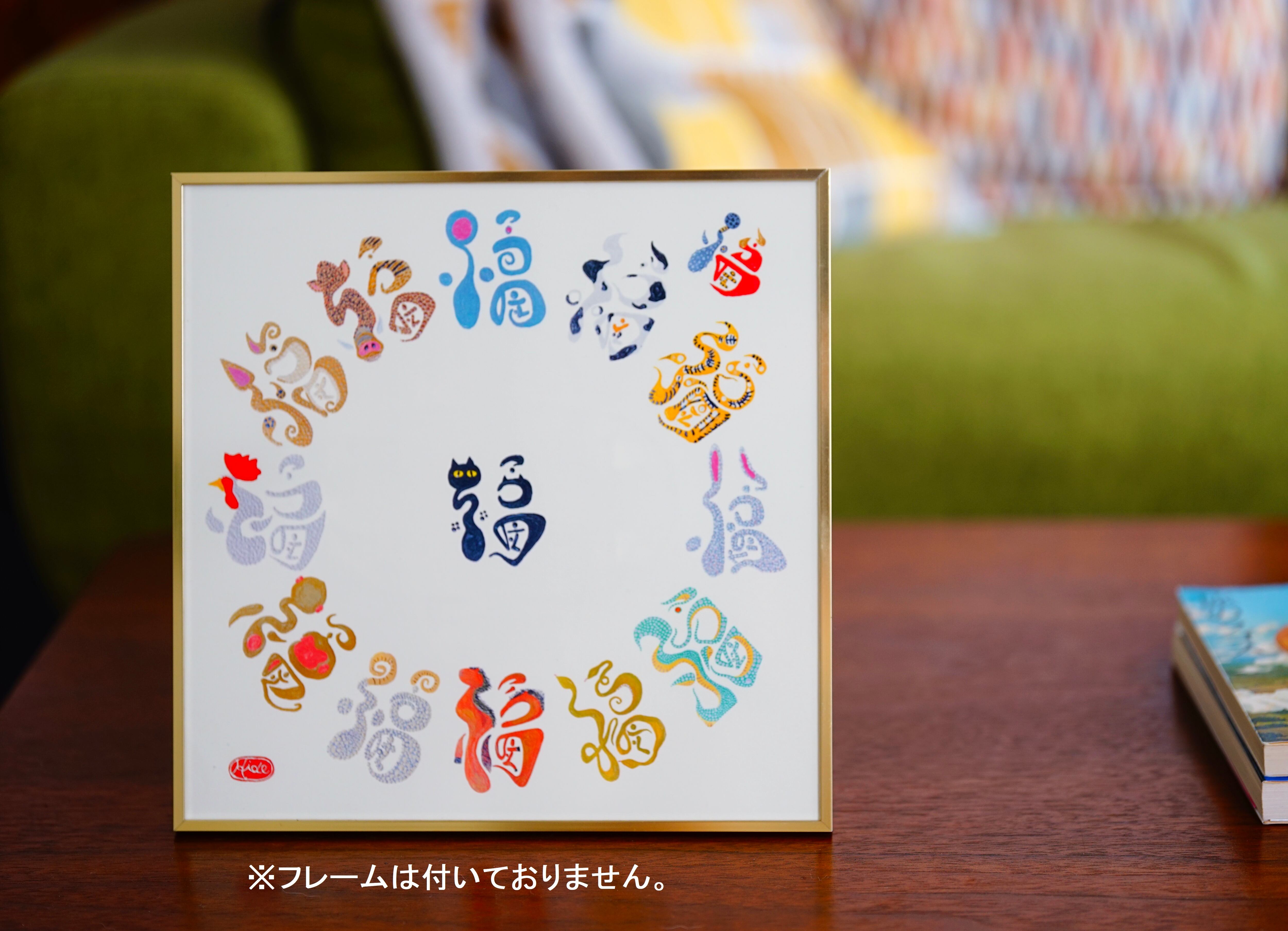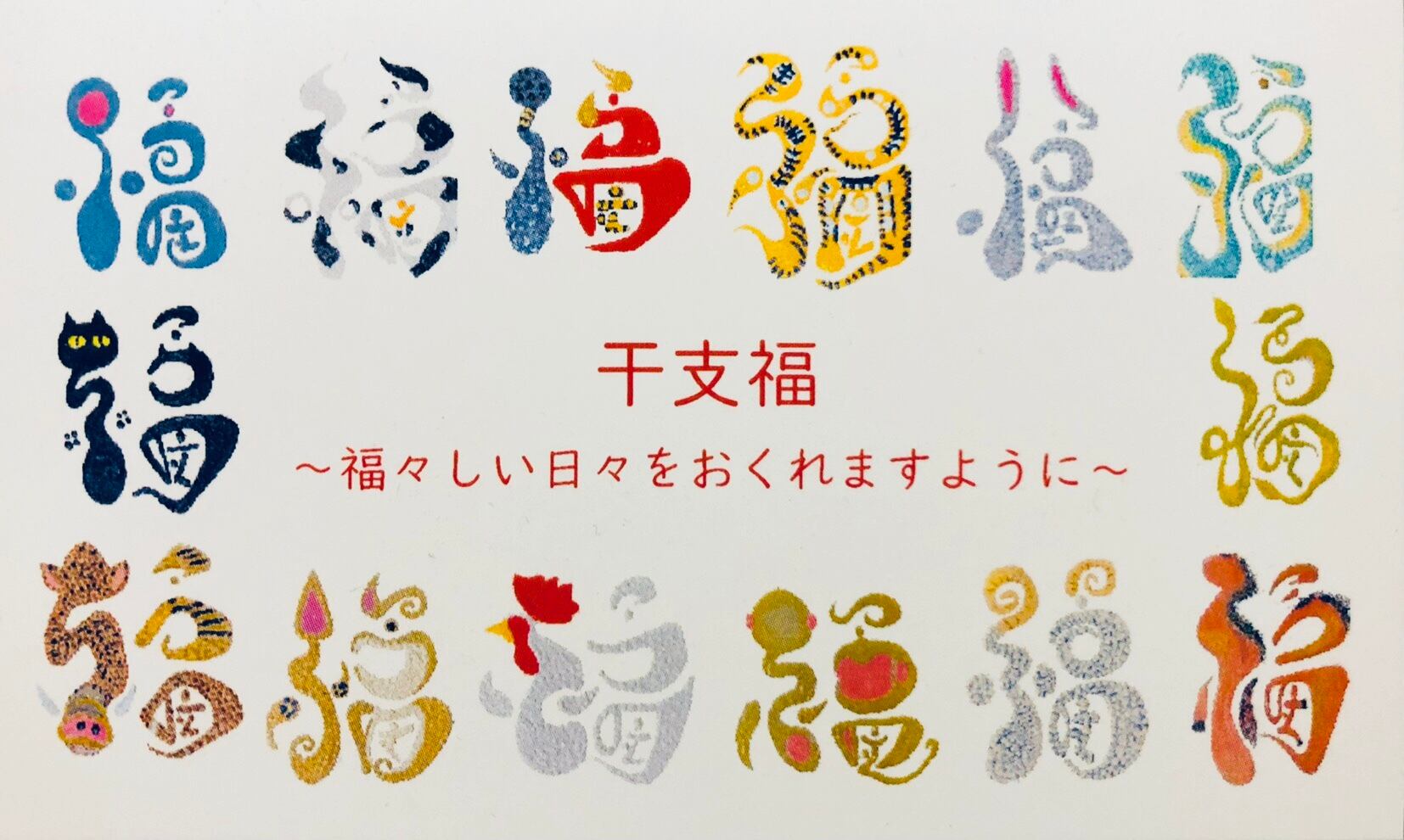
【干支福】
すべてひらがなの「ふつうのこと」で作られたこころMoji「福」ですが、
それぞれ十二支+猫と鬼をイメージした形や色で描いた作品です。
原画は一つずつが名刺サイズです。
今回は縮小した画像データを一つずつ円形に
レイアウトして、20cmの正方形の用紙に印刷しました。
【作品】
『福』~ふつうのこと~
夢や目標を抱くことは大切なこと。
想いが強すぎると「重い」になってしまい身動きがとれなくなります。
普段通りの暮らしがおくれることは「運がいい」こと。
それに気がつくと「幸福」になります。
何か特別なことではなく、何も起きないことがどれほど幸せであるか。
毎日がただ淡々と過ぎていくことが、「幸せの本質」かもしれません。